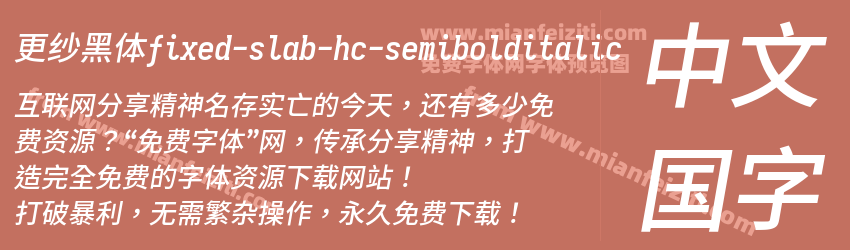
更纱黑体fixed-slab-hc-semibolditalic
字体名称: 更纱黑体fixed-slab-hc-semibolditalic
Postscript名称: Sarasa-Fixed-Slab-HC-Semibold-Italic
本款“更纱黑体fixed-slab-hc-semibolditalic”是一款书写很新颖的字体,字体大方,适合各种设计作品使用!欢迎下载!